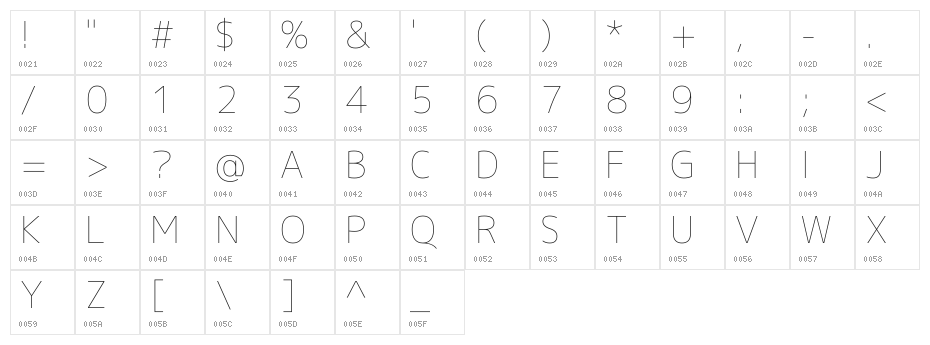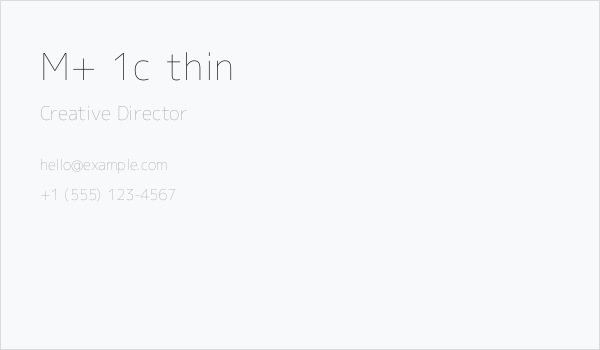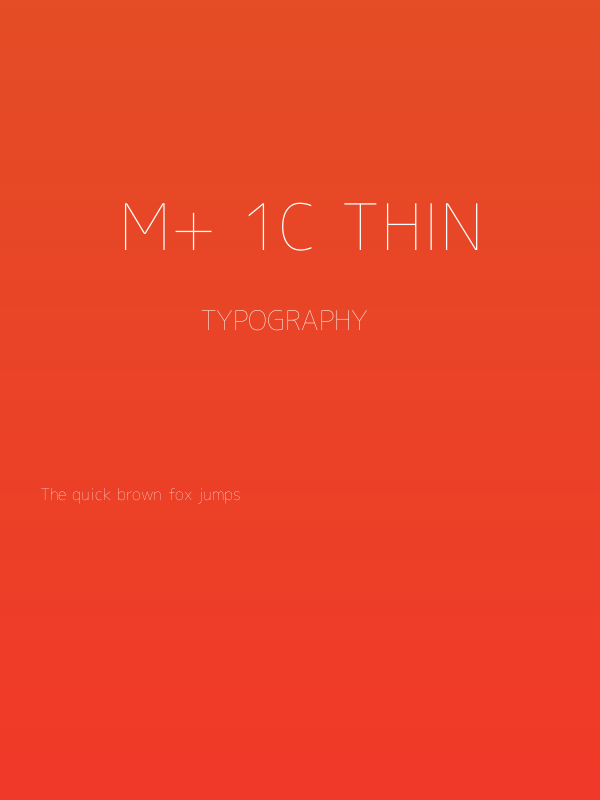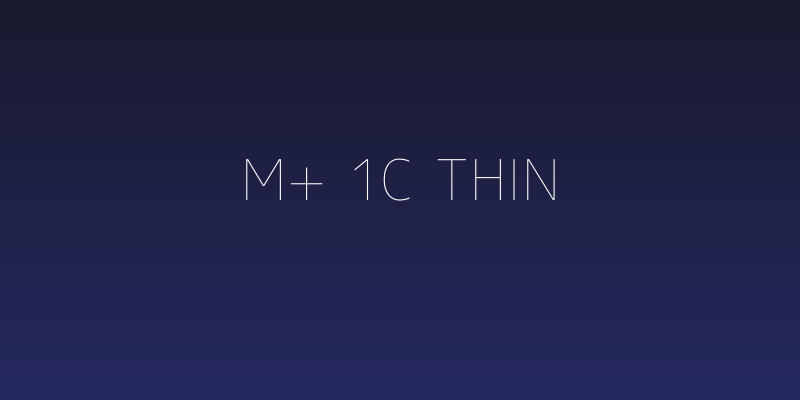
M+ 1c thin Font
| Progetti proposti | Ideal for use in digital interfaces, branding, and editorial design where a modern and clean look is desired. |